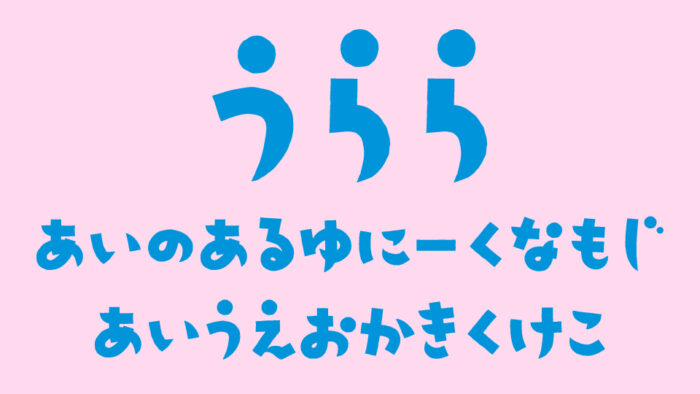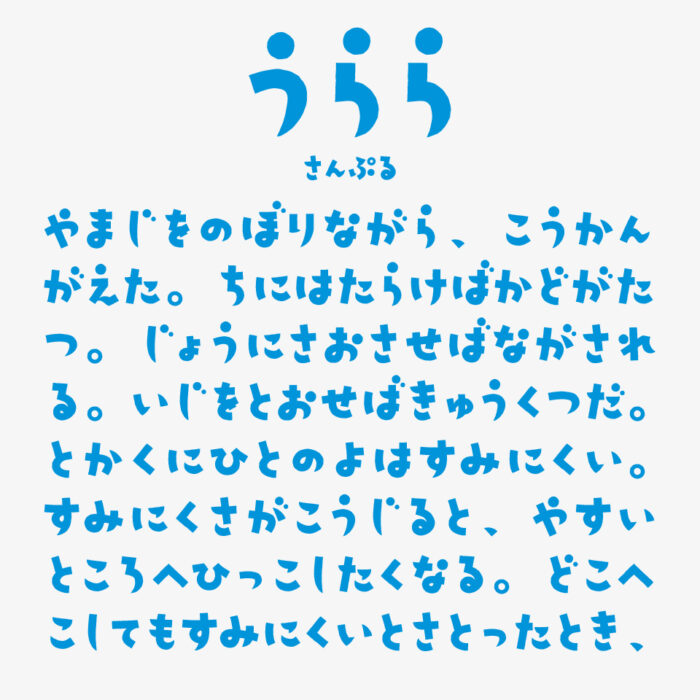
うらら
うららフォントは、X上で配布しているグレイグラフィックスさんによるコロンとした丸みと元気な印象が魅力のデザインフォントです。
ひらがなのみの収録フォントとなっています。先端が尖って、文字の濁点や部位に丸くなっているのが遊び心が満点なデザインとなっています。子供ぽい可愛さもある元気のあるフォントです。
収録文字は、ひらがなが収録されています。